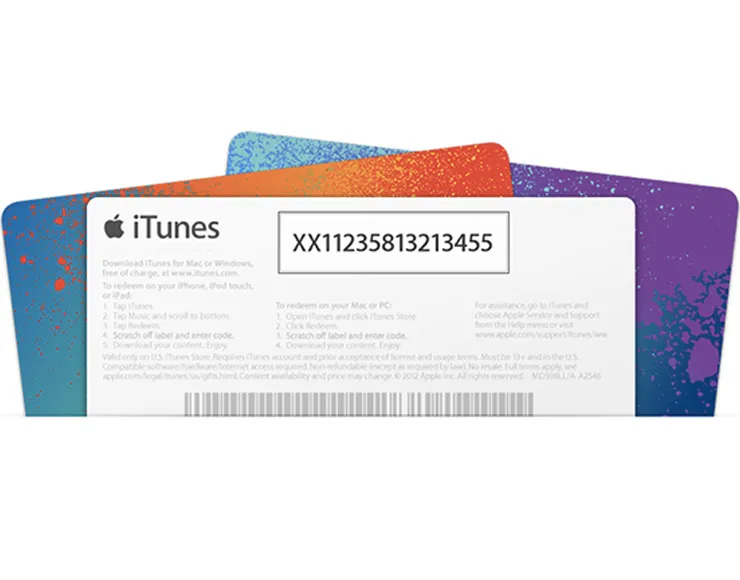
Gli sviluppatori di Equinux – software house nota per applicazioni come Mail Designer Pro 3 e VPN Tracker – hanno indagato per capire il funzionamento dei codici stampati sulle carte regalo che consentono di acquistare contenuti iTunes e Apple Music.
Con il credito di una carta regalo, lo ricordiamo, è possibile acquistare musica, film, programmi TV, app, libri, audiolibri, membership Apple Music, spazio di archiviazione su iCloud e altro. Queste carte sono vendute in vari negozi e permettono di accreditare l’importo sul proprio ID Apple. Il credito può essere sfruttato su Tunes Store, App Store, Apple Music o iBooks Store effettuando l’accesso agli store con lo stesso Apple ID.
Dopo avere acquistato una carta regalo iTunes o Apple Music, basta rimuovere o grattare delicatamente l’etichetta sul retro della carta per visualizzare il codice nascosto (16 cifre). Anziché digitare il codice manualmente, è possibile attivare l’opzione che richiama la fotocamera di Mac, iPhone o iPad e inquadrare semplicemente il riquadro intorno al codice.
Equinux ha scoperto che il riquadro in questione è obbligatorio per il riconoscimento automatico e che il font stampato sulla carte regalo non è un carattere noto ma uno specifico font a spaziatura fissa che Apple ha creato ad hoc per le carte.
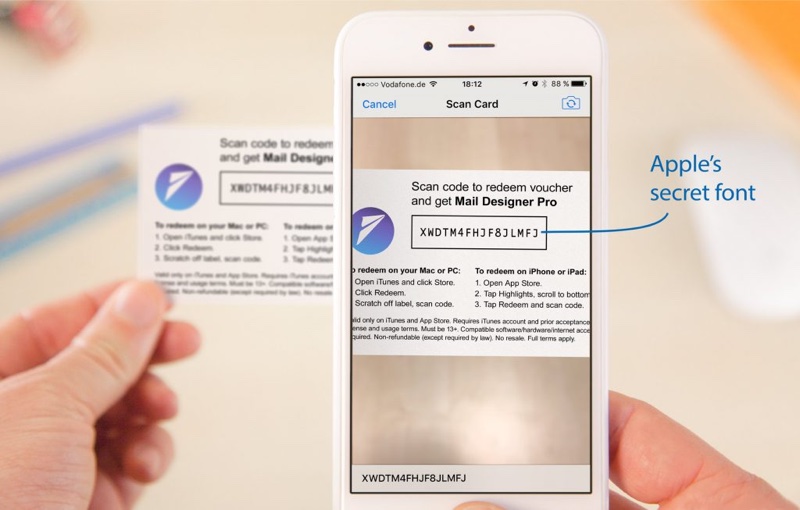
Tentativi di replicare il funzionamento delle card con font apparentemente simili quali Courier e Monaco, non hanno funzionato. All’interno di iOS e macOS (iTunes) è integrato il font sfruttato da Apple. Su Mac, i font che Apple usa per questo scopo si trovano all’interno di un framework denominato CoreRecognition.framework. È possibile visualizzare i font in questione selezionando dal Finder il menu “Vai”, scegliendo la voce “Vai alla cartella…”, incollando il percorso “/System/Library/PrivateFrameworks/CoreRecognition.framework/Resources/Fonts/” (senza virgolette) e premendo “Vai”.
Equinux spiega come deve essere composta una card perché sia riconosciuta dal sistema e mette a disposizione anche template creati con Sketch e Photoshop per gli sviluppatori che in qualche modo vogliono sfruttare il sistema di riconoscimento dei codici e creare card che possono essere scansionate e riconosciute automaticamente dalle fotocamere di Mac e iPhone.